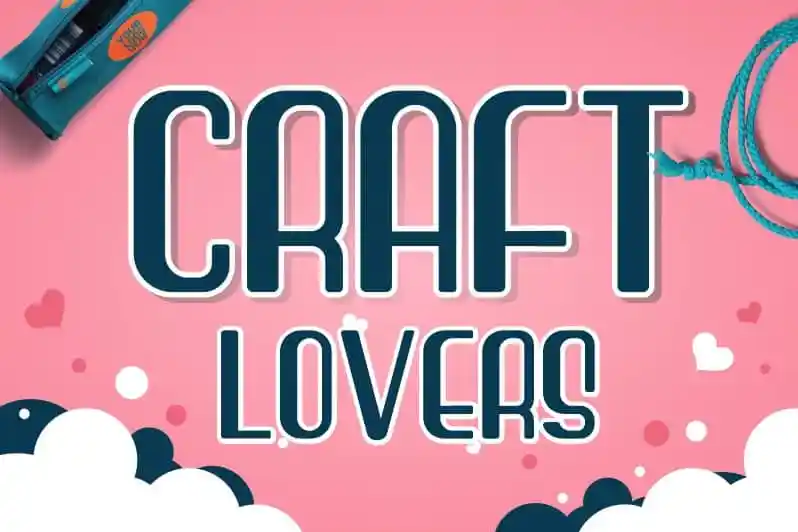
Craft Lovers Display Font – Download Grátis
A Craft Lovers Display Font é uma exuberante tipografia de destaque que celebra a beleza eclética das formas abstratas. Feita pelo font designer HansCo, esta curiosa font é perfeita para criar projetos de arte manual, panfletos, marcações, convites e qualquer outra coisa que você possa imaginar. Através desta font, seus novos projetos ganharão destaque, trazendo um toque único ao seu design. Ideal tanto para quem aprecia a arte manual quanto para criadores de design, Craft Lovers é uma excelente escolha para personalizar sua identidade visual e tornar suas criações ainda mais únicas.